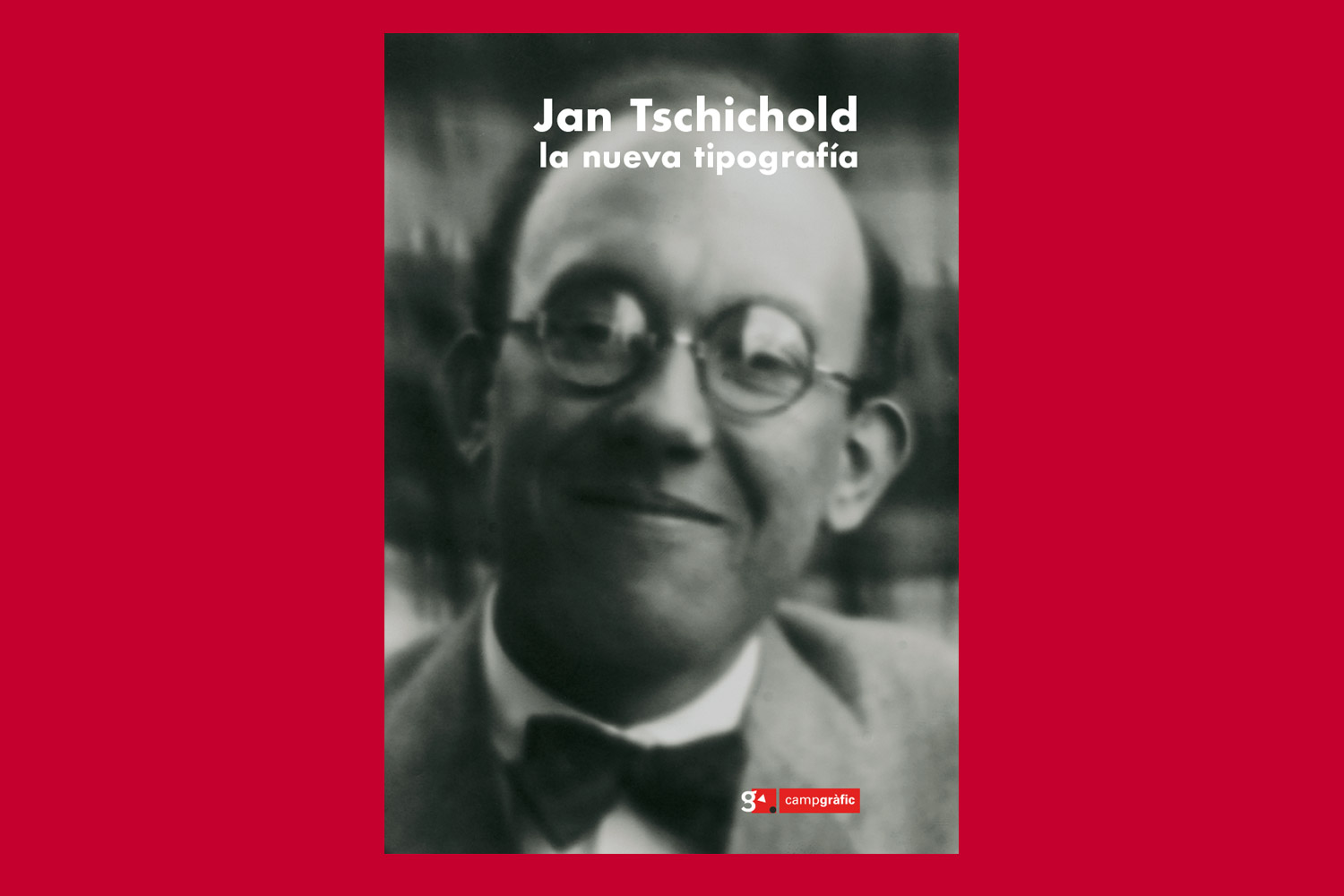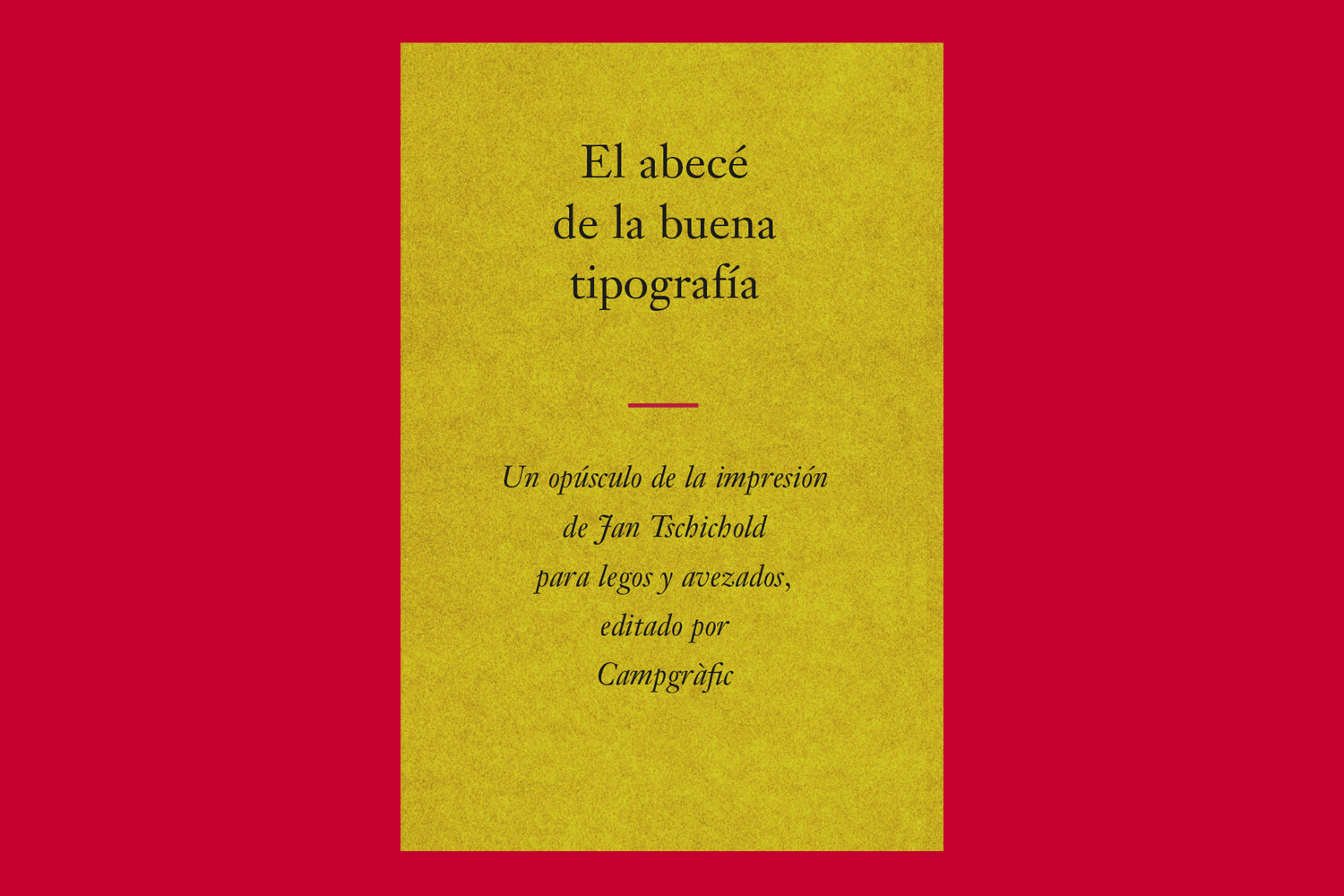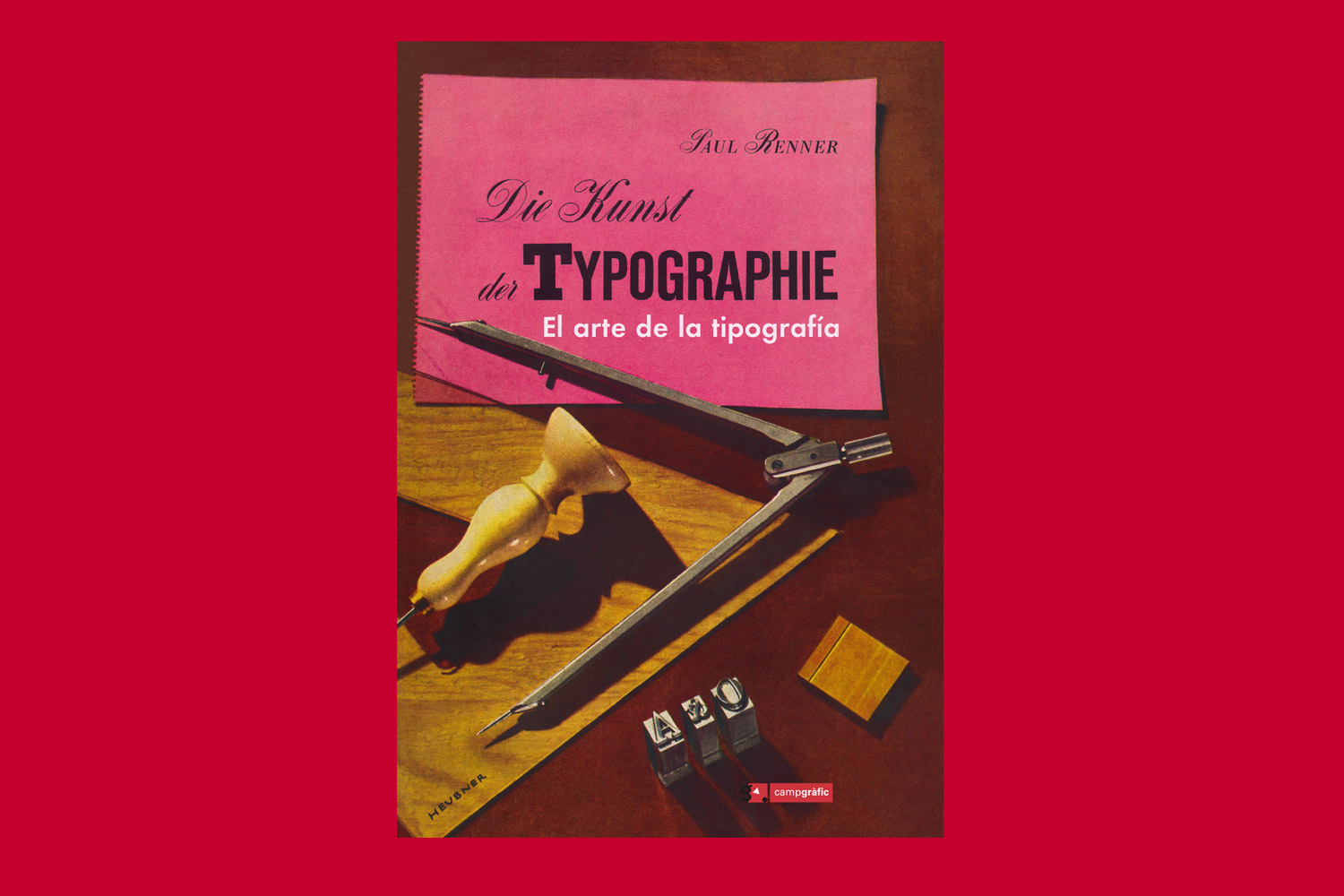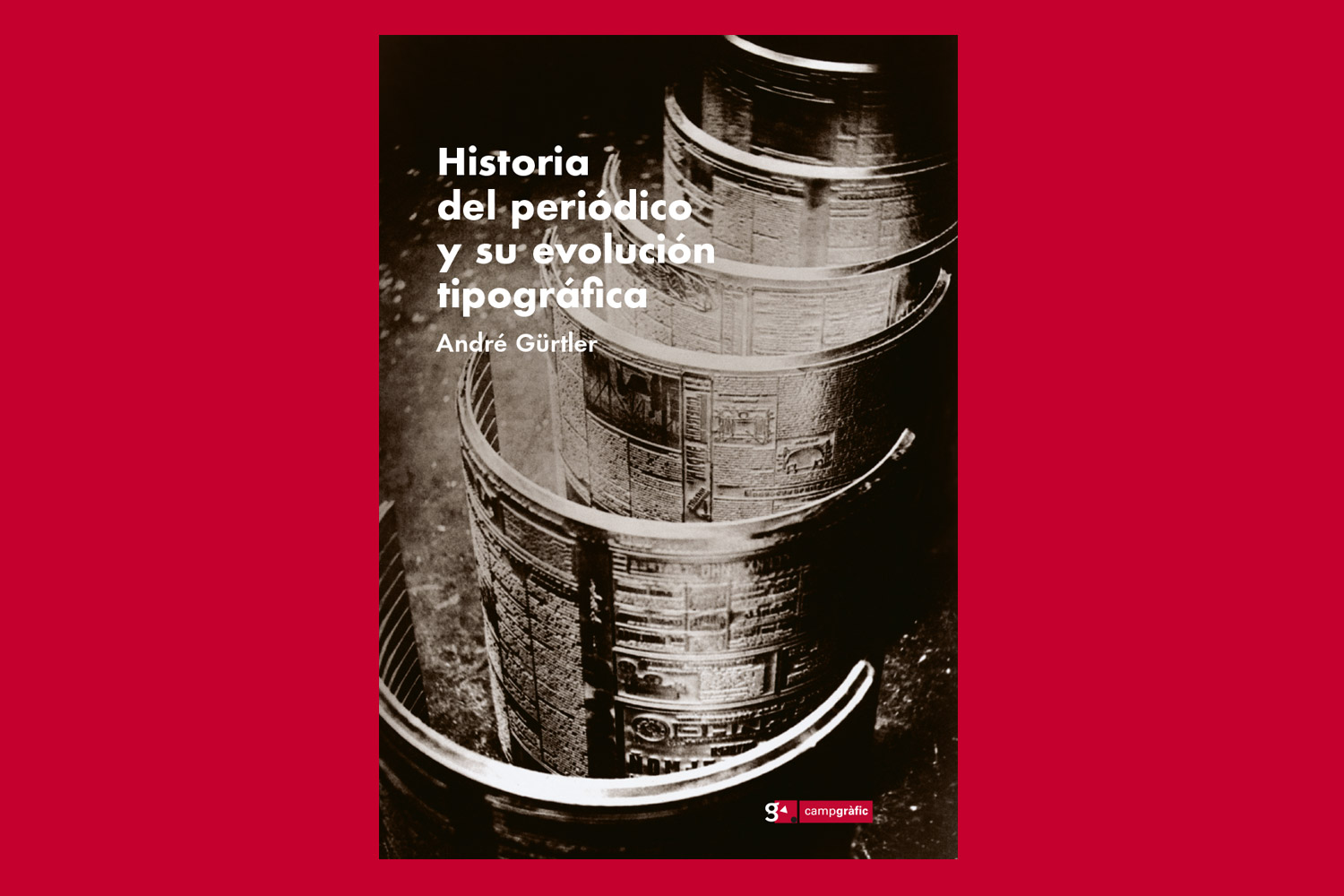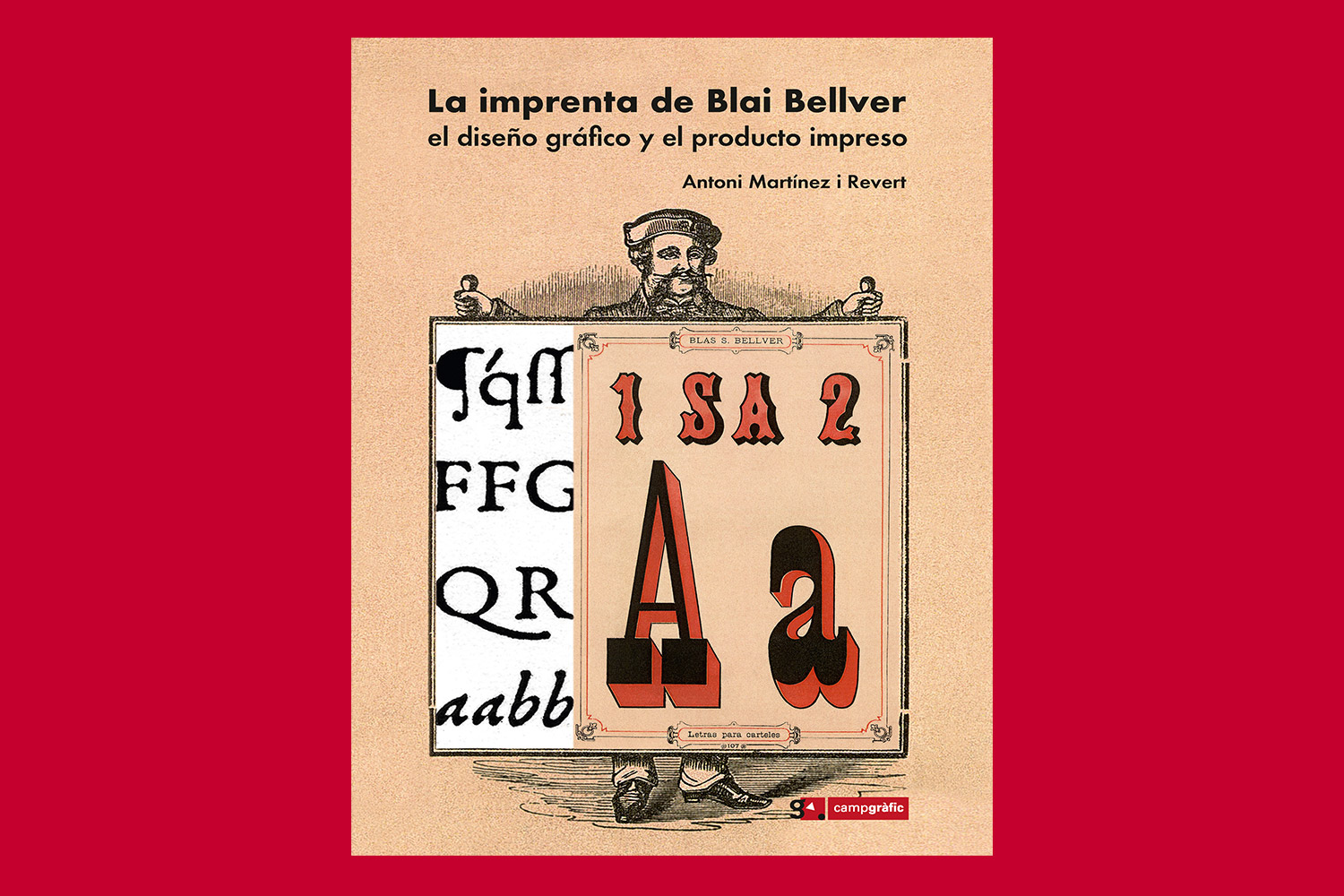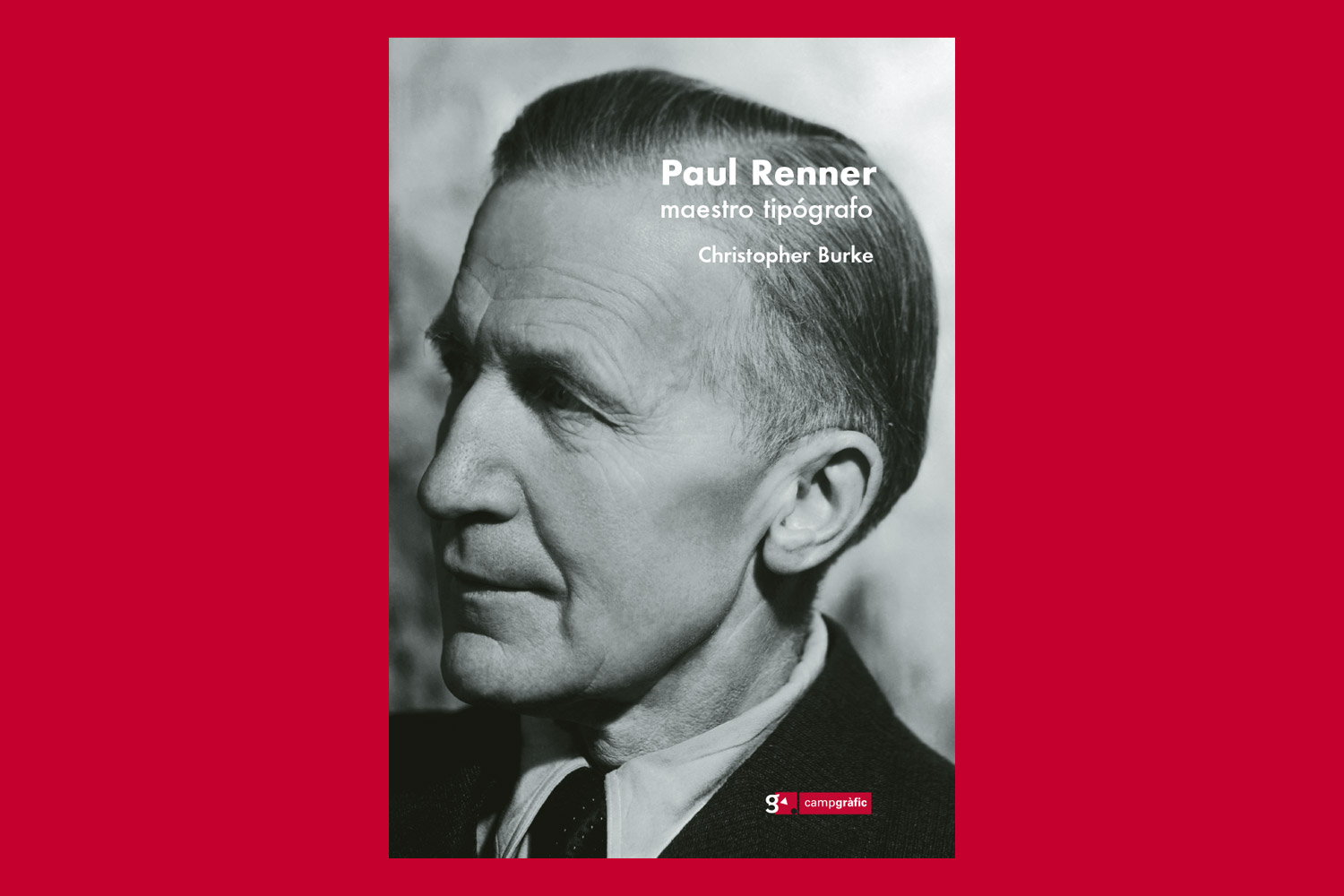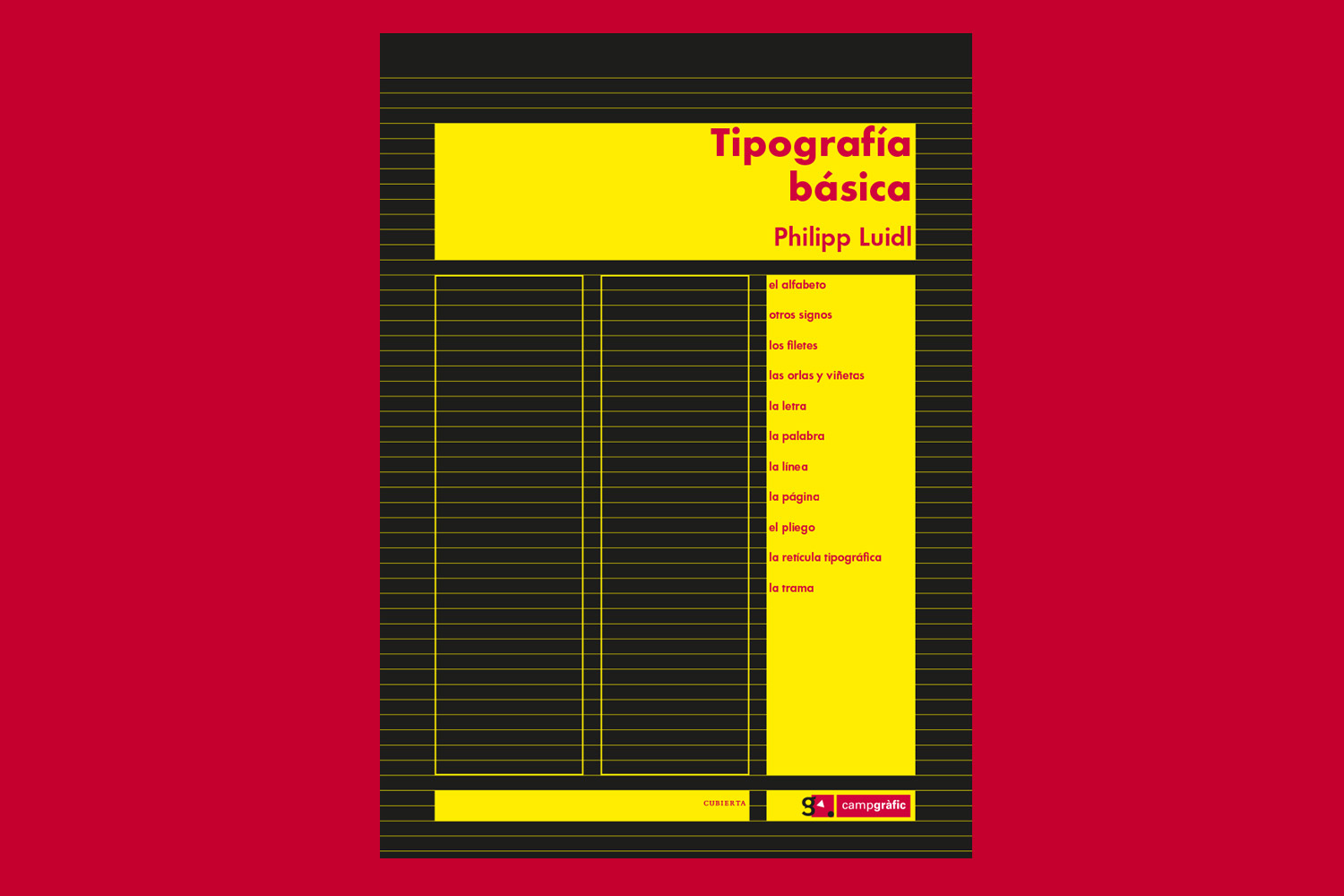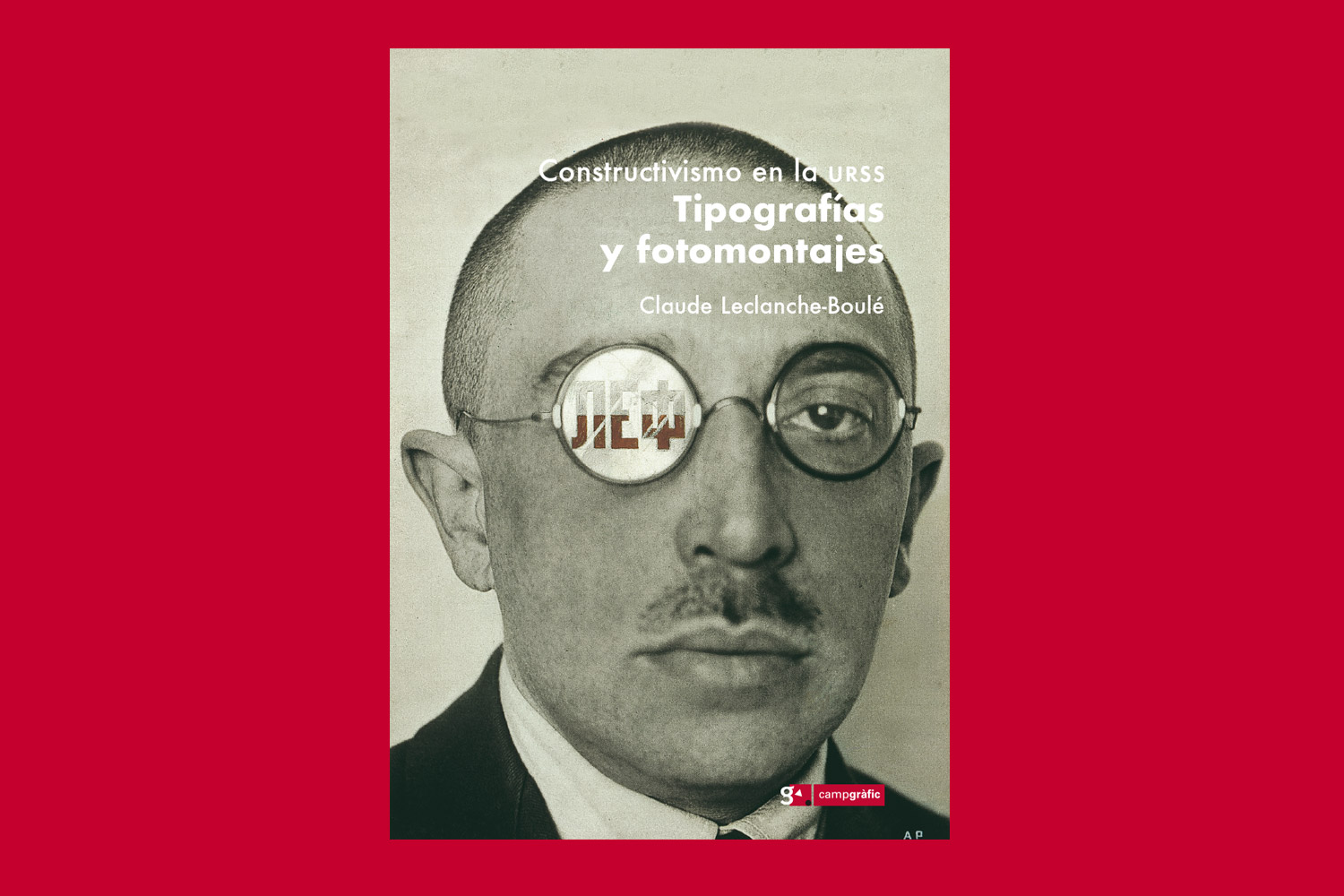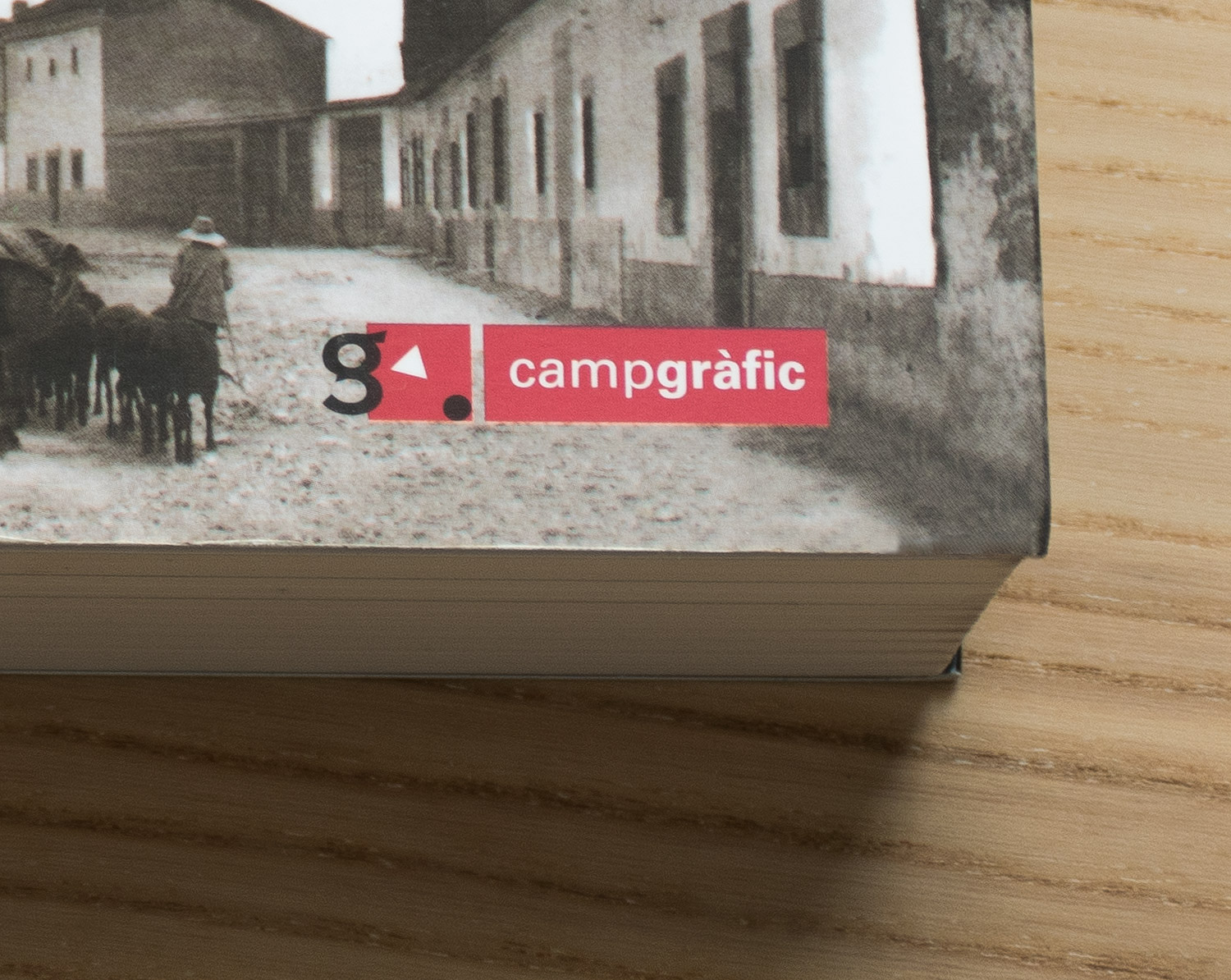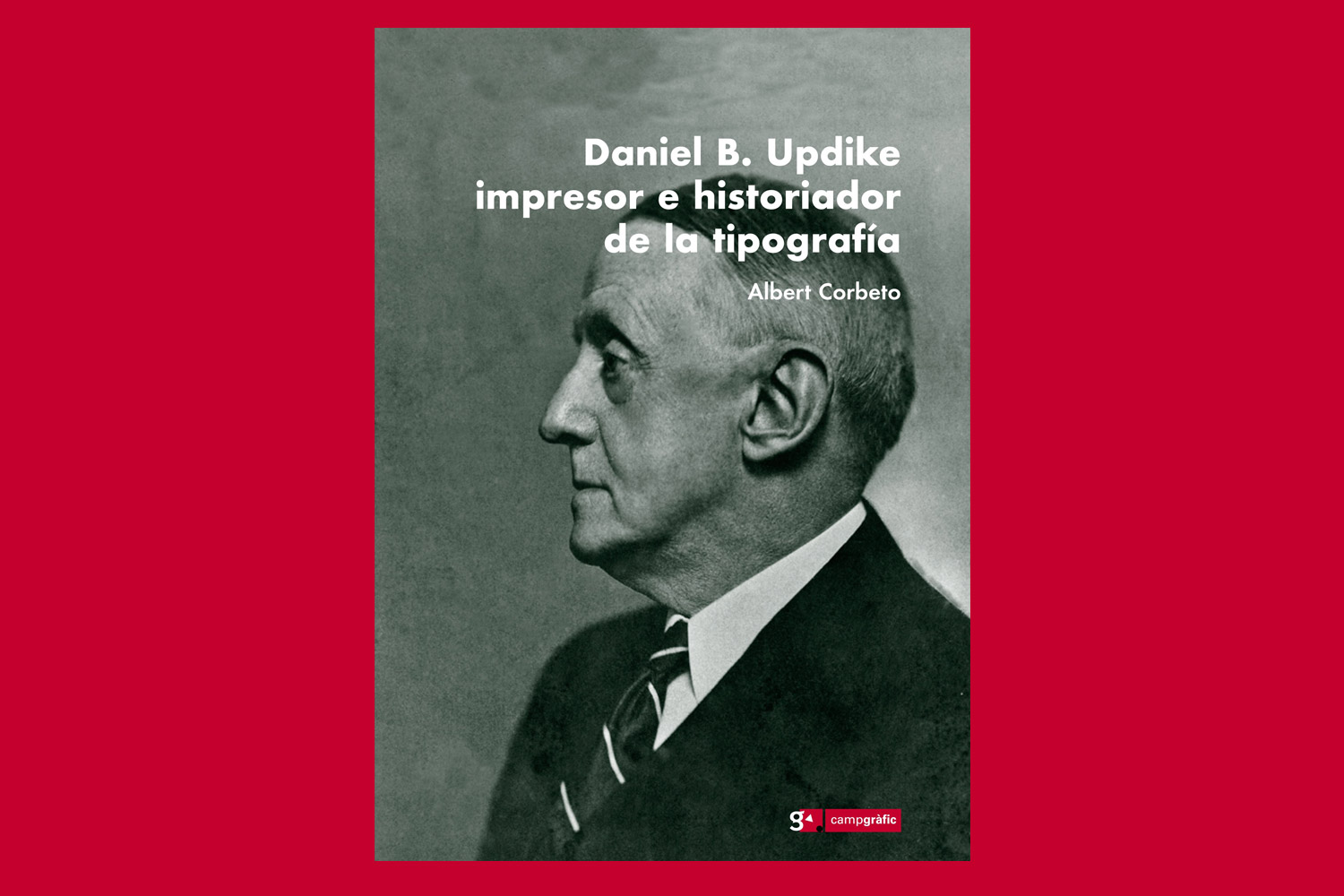
Campgràfic es sinónimo de tipografía, de impresión y, sobre todo, de entusiasmo… El necesario e imprescindible para apostar por la divulgación de un área del diseño que, allá por 1999, contaba con muy poca repercusión si la comparamos con el interés que suscita hoy día. “Buscábamos ofrecer una respuesta a por qué en la mayoría de las librerías europeas existían apartados para ‘los libros que hablan sobre libros’, y por estos lares nada había. O haciendo honor a la verdad, esporádicas ediciones sin seguimiento”.
Después de llevar más de una década recomendando en clase su imprescindible Manual de Tipografía o haber descubierto los vericuetos del diseño de libros de la mano del magnífico El diseño de libros: práctica y teoría, charlar con el equipo de esta editorial valenciana, es como redescubrir a un viejo amigo al que hace tiempo que no ves.
De hecho, hace muy poquito os hablábamos en este vuestro blog de El ABC del lettering de Iván Castro, uno de sus últimas y más exitosas referencias.
Pero vamos por orden, que nos liamos.¿Qué y quiénes son Campgràfic?
“A mitad de camino entre 1999 y 2000, nos juntamos tres personas cuya ligadura era la letra. Aunque el punto de partida tenía asientos diferentes.
Fèlix Bella había ligado sus estudios al peritaje químico, aunque nadie debe llevarse a equívocos, al relacionar química y papel, para encontrar el punto de unión entre los estudios y la dedicación profesional, que por aquellos años ya se encontraba inmersa en el mundo de las artes gráficas tanto en su vertiente laboral –trabajaba en la Generalitat – como en sus inquietudes personales e ideológicas, pues más de una revista de carácter político antes de llegar al ciclostil había pasado por sus manos.
José Luis Martín, compañero de recio abolengo impresor, se había criado entre la tinta y la minerva, entre cajas, altas y bajas, para saborear las nuevas tecnologías de la cuatricromía, el directo a plancha o la impresión digital. Pero antes que deus ex machina, se empapó de filosofía en la universidad para, en una mixtura necesaria, acabar lanzando uno de los máster de diseño gráfico más sólidos de la universidad española, en el que es profesor desde su primera edición en la Universidad Politécnica de Valencia.
Por su parte, Xavier Llopis tiene en la traducción y la corrección de textos su entrada en el campo tipográfico. En las horas libres de sus estudios de filología hizo de picador, lector, atendedor… en una imprenta. Poco después, y recién licenciado, se inclinaría por la corrección de textos, y eso le conduciría a formarse en asesoramiento lingüístico, tipografía y a dar clases de traducción en la UJI, al tiempo que, sin separar la teoría de la práctica, corregía con denuedo páginas, documentos y libros”.
Desde estos tres puntos de vista, el del diseñador, el del impresor y el del corrector en 1999 se cruzarían nuestras visiones para concretarse en CampgràficPensamiento tipográfico y pedagogía como base
“Nos interesó participar en un debate público que se escondía, aparentemente, bajo el territorio de la incapacidad –se nos decía– de gestar una mínima racionalidad en la tipografía, el diseño gráfico e incluso en la caligrafía.
Nuestro objetivo era sacar a la luz aquellas propuestas que quedaban amazacotadas en las baldas universitarias. Asimismo, quisimos ofrecer algunas de las grandes obras que en este campo habían aportado gran parte del pensamiento en Europa y los Estados Unidos.
Así nos decidimos a iniciar una doble vía de publicaciones. Por un lado, ediciones de pensamiento tipográfico, y, por otro, obras pedagógicas. Esta mirada doble pretendía ofrecer herramientas (manuales) a los estudiantes y profesionales, sin dejar de lado a quienes buscaban en la evolución cultural respuestas a ciertas cuestiones (¿Por qué la letra gótica está asociada popularmente a lo alemán? ¿Por qué la letra romana mayúscula tiene un carácter institucional? ¿Cuál es la razón por la que ciertos movimientos neonazis se inclinan por la letra gótica?). En paralelo, el pensamiento tipográfico surgía como una necesidad en muchos casos desconocida. Así plantemos, con las actualizaciones pertinentes, el pensamiento de Paul Renner, Jan Tschichold, Otl Aicher o J.M. Pujol”.
RA: En los últimos años, la tipografía ha adquirido una relevancia de la que carecía previamente y se ha reavivado el interés por la misma entre la comunidad gráfica. Vosotros que lleváis apostando por aportar racionalidad a su estudio, etc. desde hace más de 15 años, ¿cómo veis este renacimiento? ¿Pensáis que se trata de una moda pasajera o que ha venido para quedarse?
“El proceso de cambio de paradigma cultural en el que nos encontramos inmersos ha modificado muchas estructuras. Entre ellas la de la tipografía. En ningún caso consideramos que se trata de una moda, más bien diríamos que ha salido a la luz, un interés que parecía escondido en los talleres de imprenta y en la alta cultura. Hoy es más popular. El debate está servido. Y no solo en la comunidad gráfica sino que empieza a participar en el mismo mucha gente. Nuestra aportación a este debate ha sido incorporar herramientas, ideas, que han forjado el gusto tipográfico en el último siglo y cómo se ha instalado este en la sociedad”.
Los favoritos de Campgràfic por Campgràfic
RA: Si tuvierais que elegir vuestros cinco libros favoritos de Campgràfic, ¿cuáles serían?
RA: Para acabar una pregunta indispensable… ¿A qué tipografías le tenéis especial cariño y por qué?
La lecturabilidad de la Celeste de Chris Burke está entre nuestras opciones, lo mismo que su contraste con la Futura. Pero los afectos tipográficos los determina el libro y su planteamiento. No se trata tanto de gustos personales, como de tipografías que mejor se adapten al libro que estemos trabajando. Cada libro, tiene su tipografía, como nos enseñó Jost Hochuli.